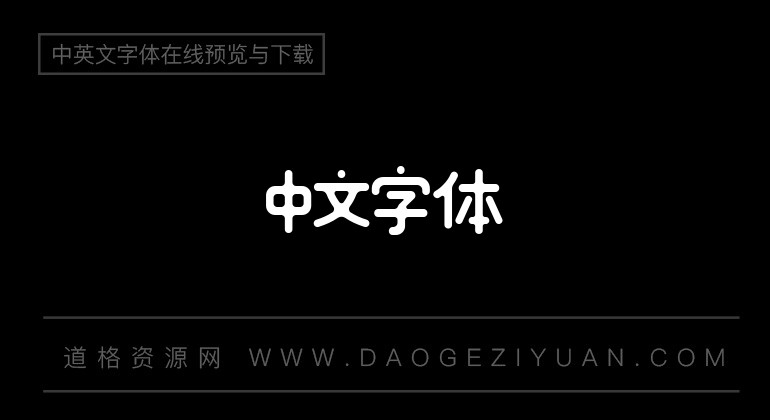
造字工房喜月体是一款由日本造字工房设计的日本传统风格字体,可以用于日文书写、印刷、网页设计等多种用途。该字体笔画细腻,符号和拼音都设计得十分精致,可以很好地表达日本传统文化的精髓,是一款非常适合日文书写和排版的字体。文件名:ZaoZiGongFangXiYue-2.ttf
造字工房喜月体是一款非常不错的手写艺术字体,具有很好的视觉感,适合于文化类的宣传设计、商业类品牌的广告和产品包装设计以及个性化文字排版等较多场景。